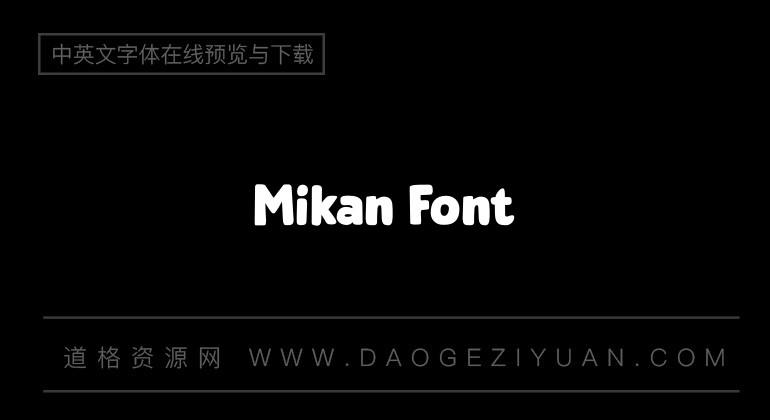
Mikan Font
Mikan Font是一种日本的免费字体,由MikanFonts Project开发。该字体的设计以汉字的简洁美和日本的传统文化为特点,同时也融合了现代感。Mikan Font包含了日文、英文、数字和基本的符号,支持多种字重和变体,可用于不同的设计需求。该字体的特点是易读,适合用于各种场合,如海报、广告、印刷品、网页设计等。此外,Mikan Font还支持商业和非商业用途,可以在网站上免费下载和使用。
Mikan Font是一款非常不错的手写艺术字体,具有很好的视觉感,适合于文化类的宣传设计、商业类品牌的广告和产品包装设计以及个性化文字排版等较多场景。